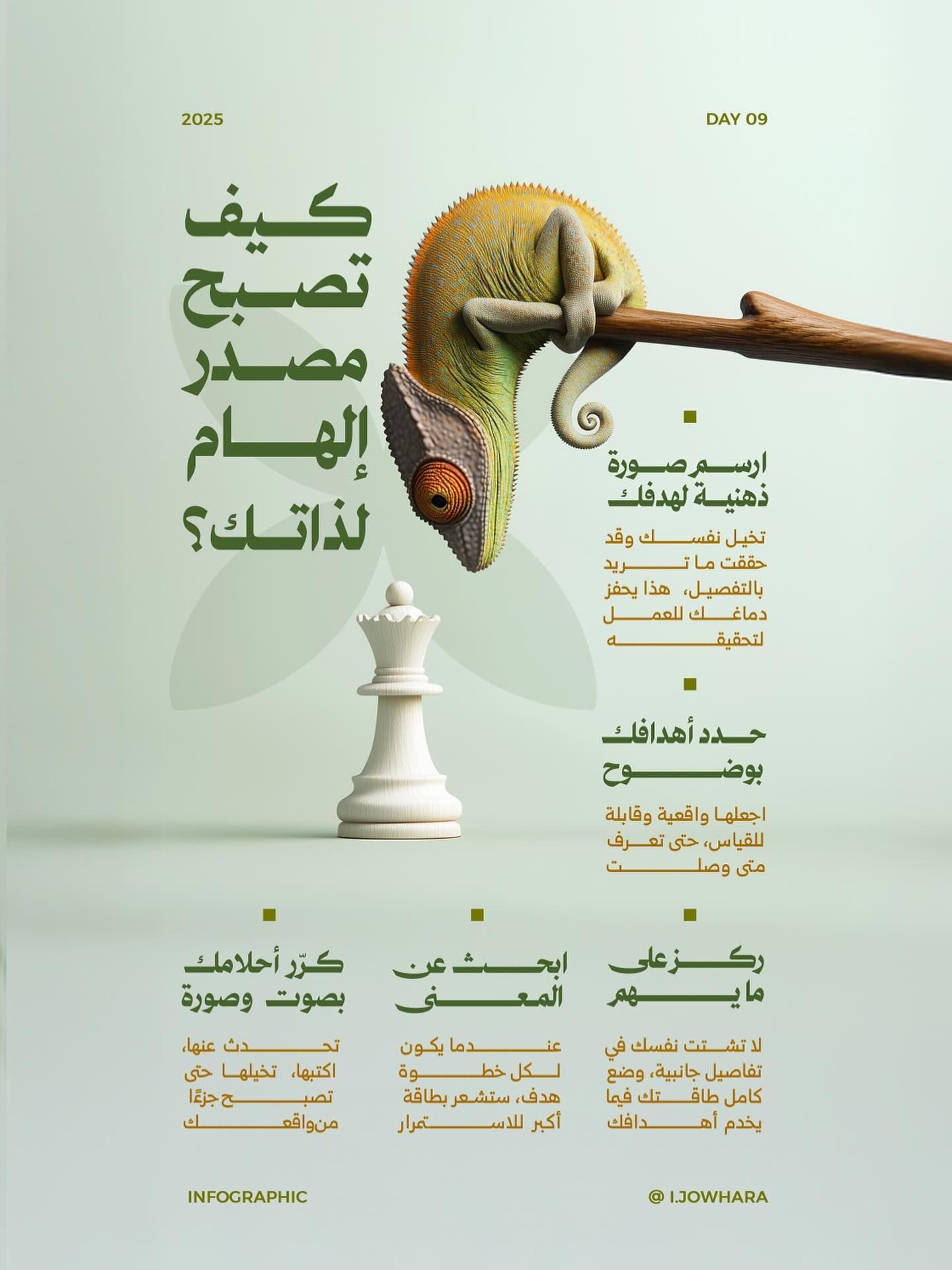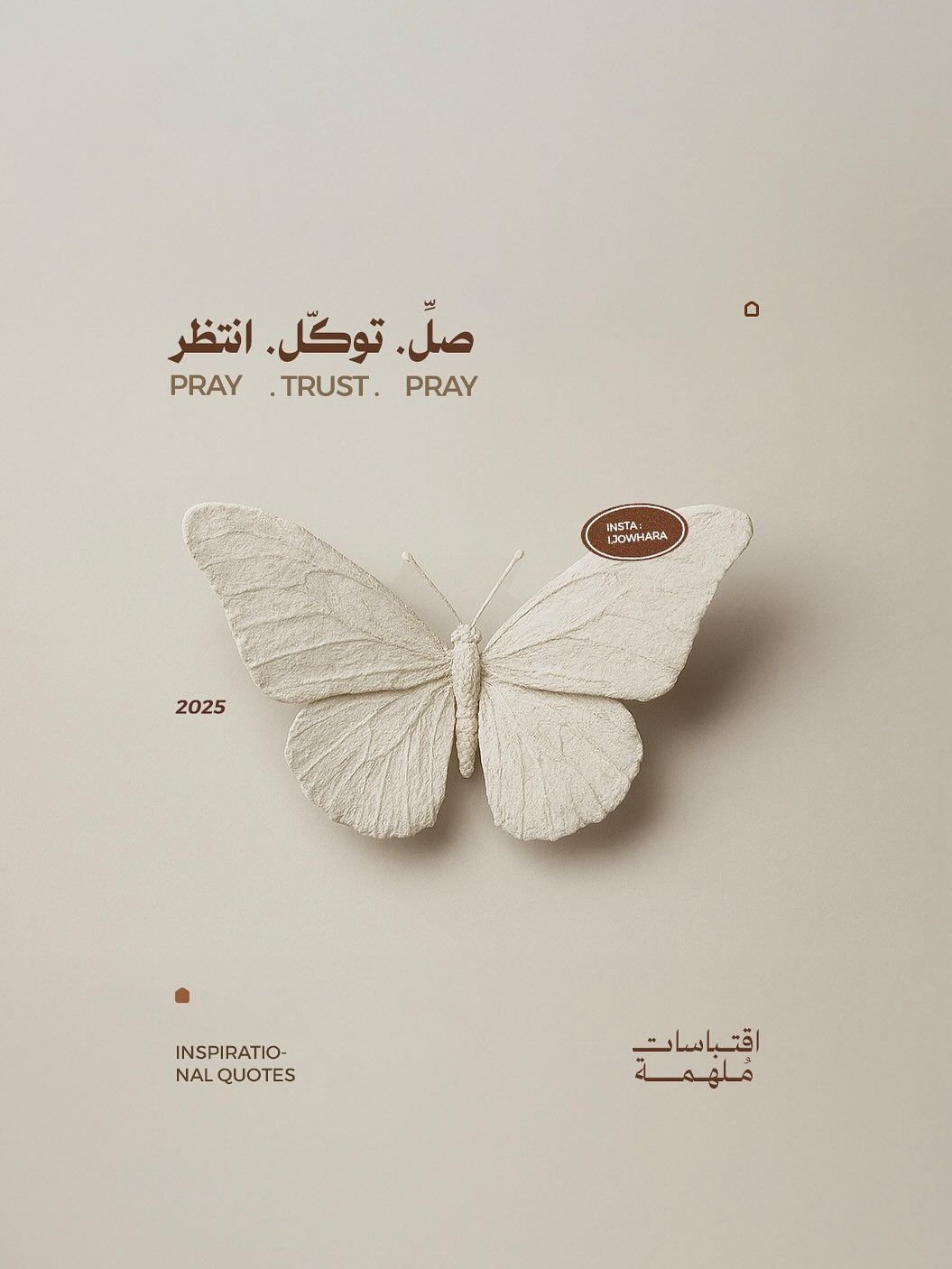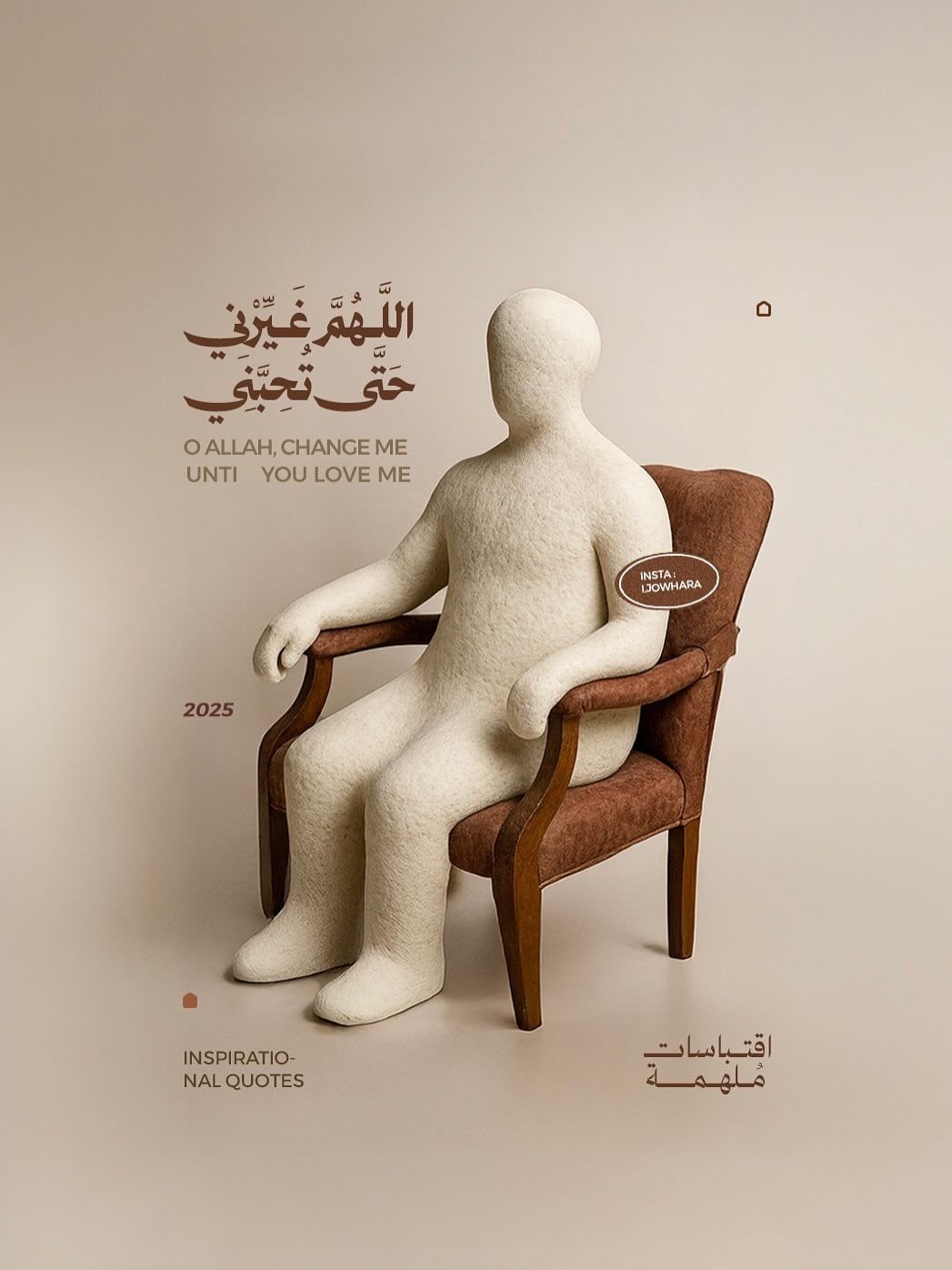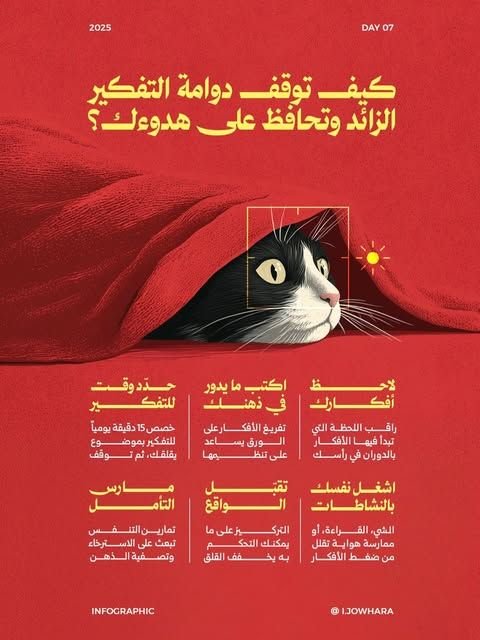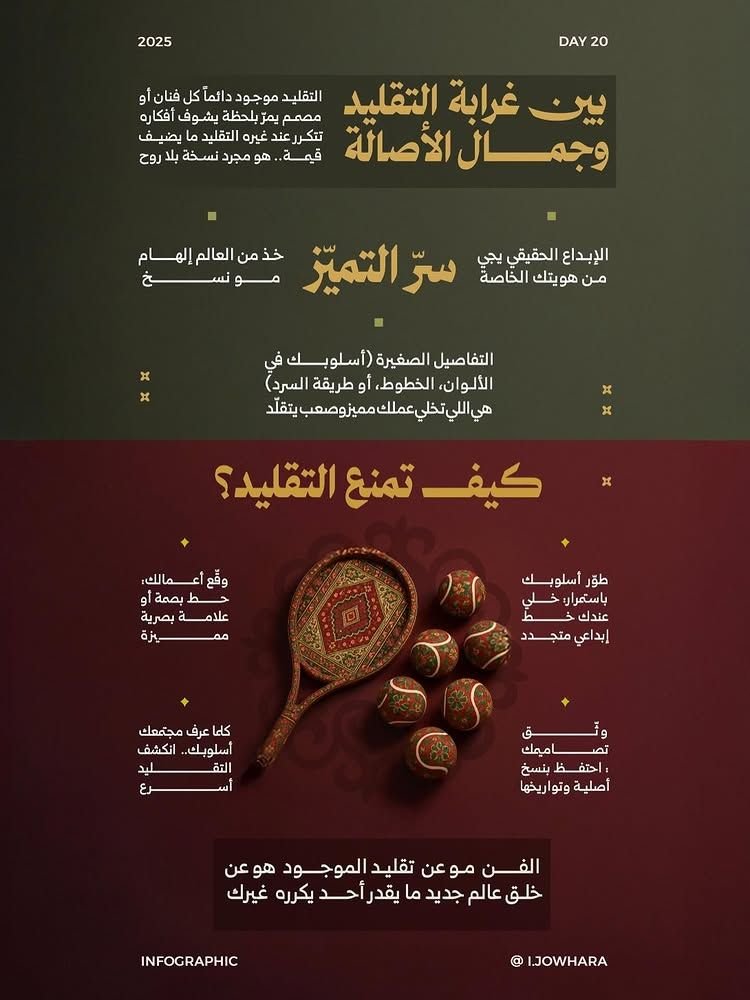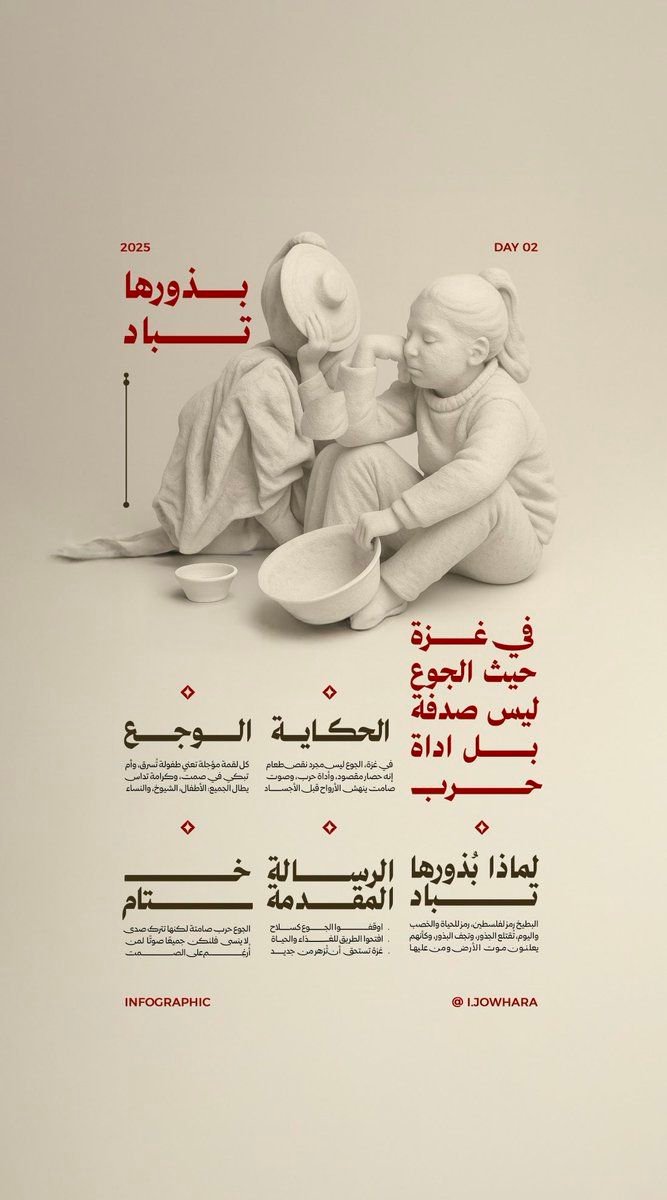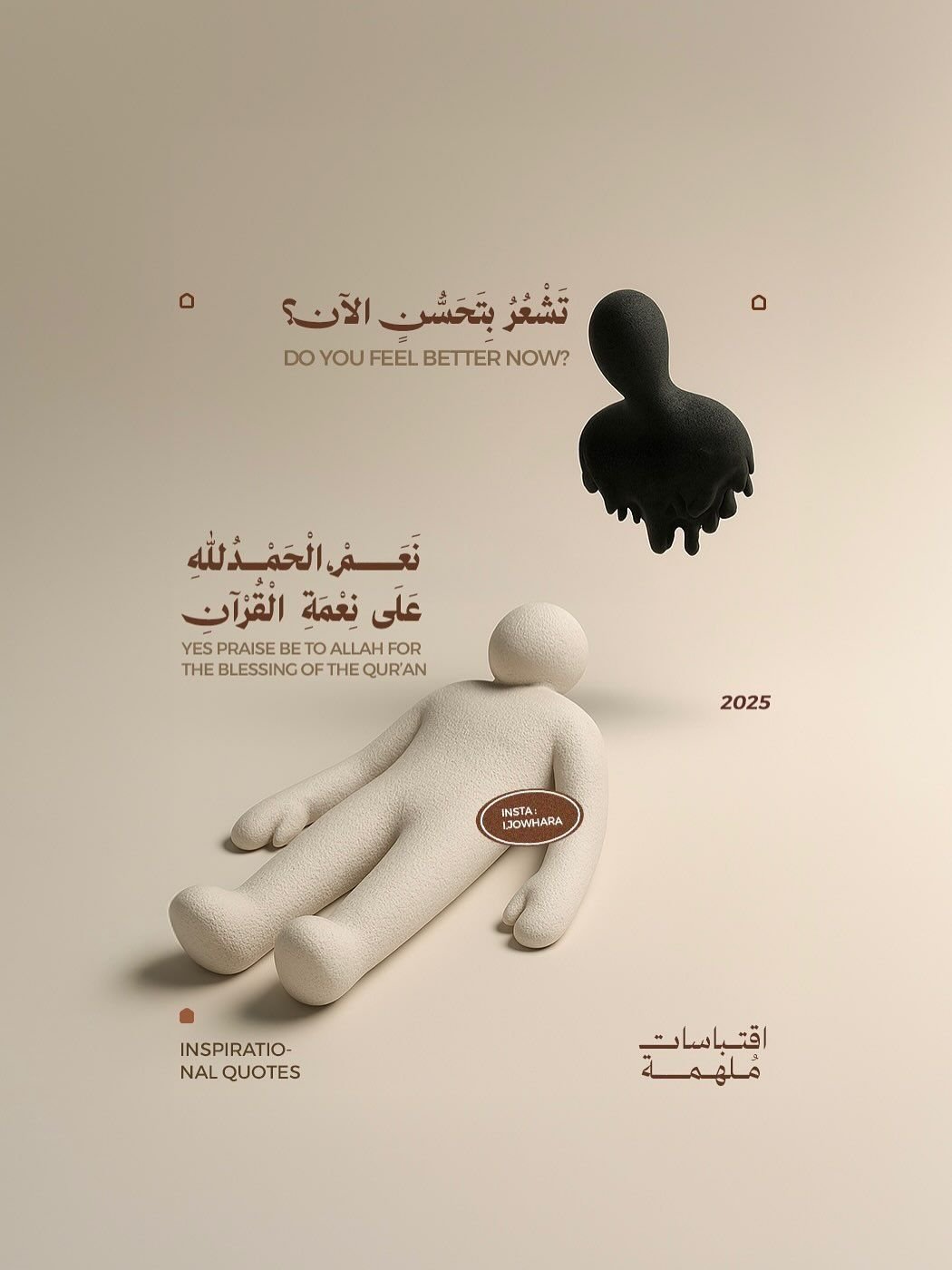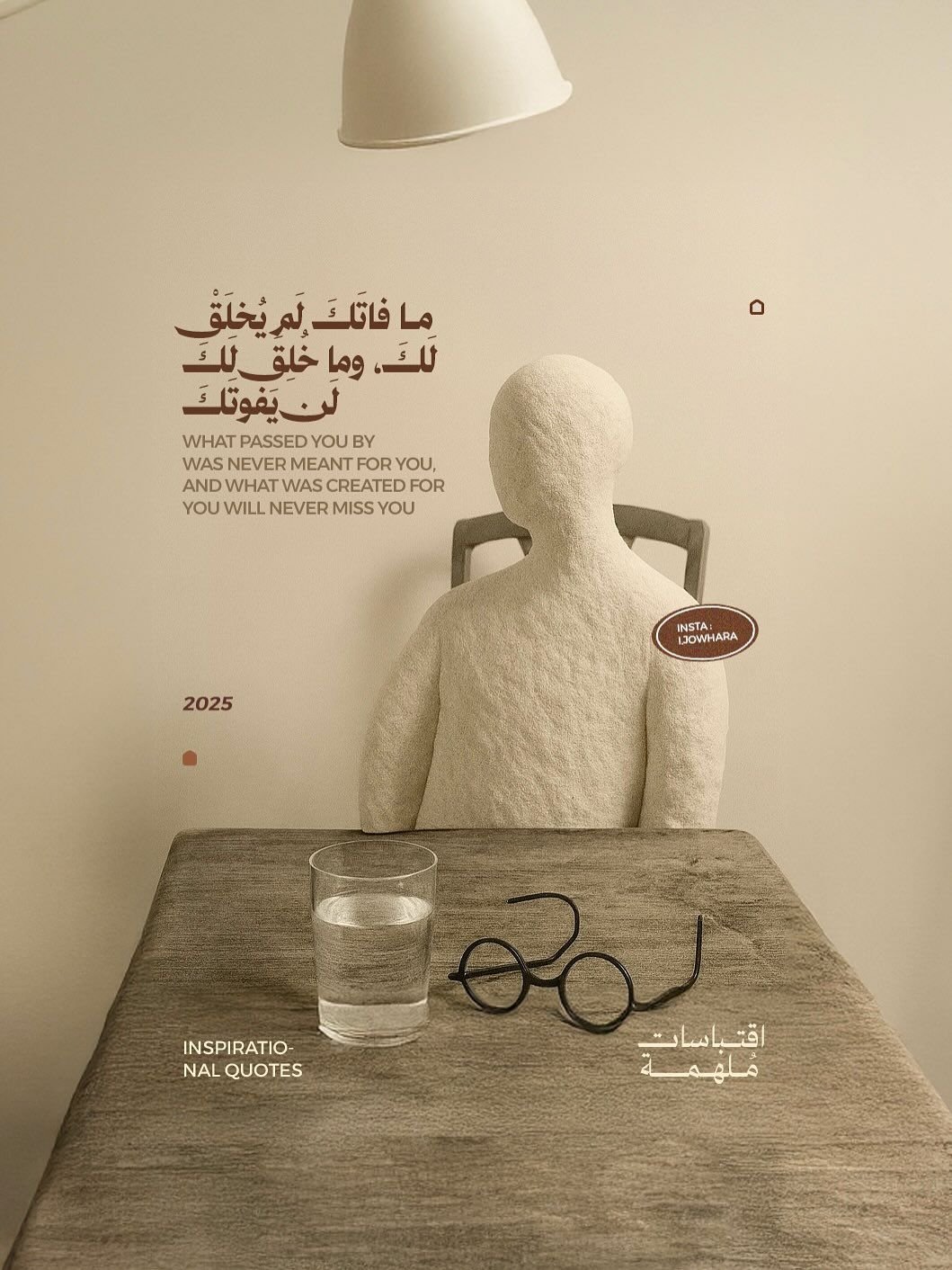
خط رواسي في أعمال جوهرة — خط نسخ عربي
رواسي عربي هو خط عربي احترافي مستوحى من النسخ المسطري، يتميّز بتصميم قوي وحواف حادة تمنحه حضورًا بصريًا واضحًا ومؤثرًا. يضم الخط 7 أوزان متكاملة توفّر مرونة عالية في الاستخدام عبر مختلف المشاريع، من الشعارات والهويات البصرية إلى المواقع والتطبيقات والمطبوعات. يجمع رواسي بين وضوح القراءة، الانضباط الهندسي، والأناقة الحديثة ليكون خيارًا مثاليًا للتصميم التجاري والمؤسسي.